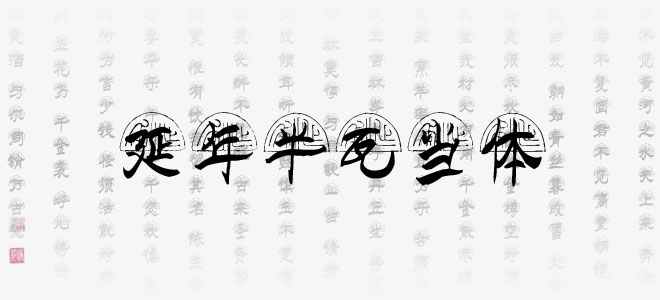
本款“延年半瓦當(dāng)體”是一款書寫很新穎的字體,字體上半部分帶有陰影,字體大方,適用于海報(bào)、電商海報(bào)設(shè)計(jì)、店鋪設(shè)計(jì)、標(biāo)志設(shè)計(jì)、字體設(shè)計(jì)等領(lǐng)域,歡迎需要的朋友下載使用。
延年半瓦當(dāng)體